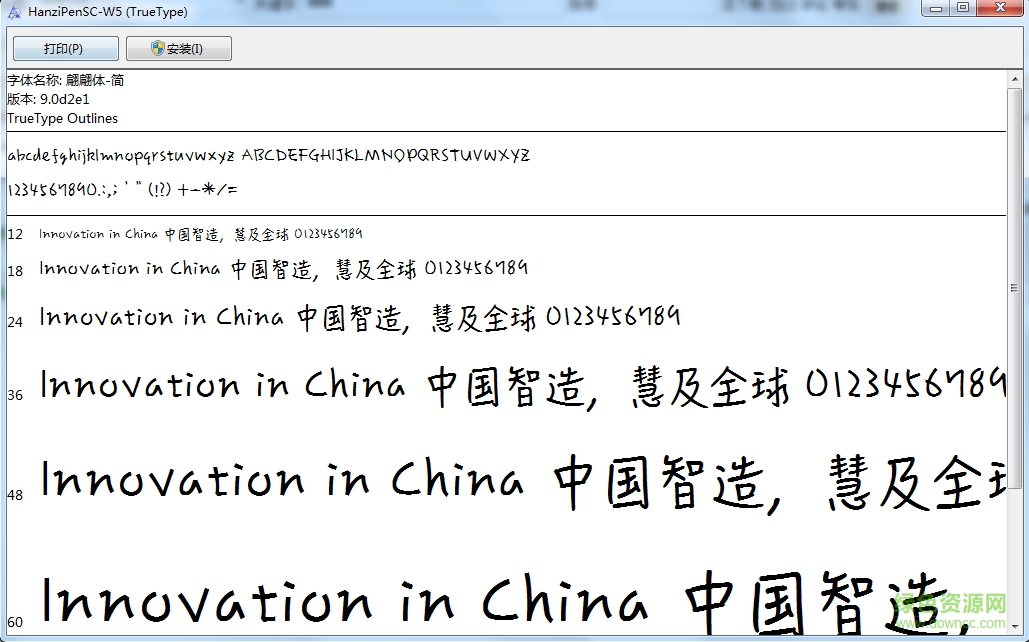
hanzipensc w5是什么字體?hanzipensc w5字體是一款比w3稍微粗一點的華康翩翩體,線條隨意自然,筆畫灑脫,類似于一般的手寫體風(fēng)格,歡迎大家免費下載!
手寫體文字是用“美工筆”在紙上寫出來的,可能一個字會寫幾十遍或者更多,之后再從中間選出寫的比較可以接受的拍照,上傳到電腦上用photoshop處理后制作而成。